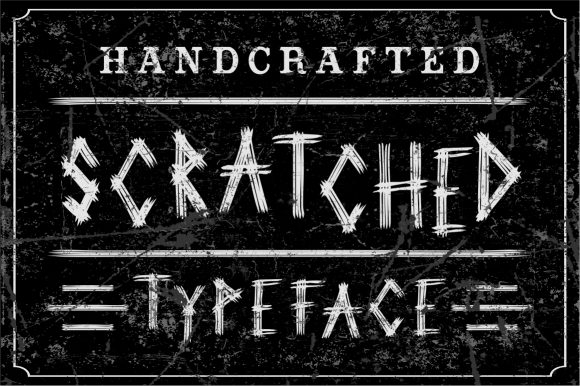
Handcrafted Scratched Typeface
Die richtigen Designelemente zu finden, kann eine Herausforderung sein, aber Handcrafted Scratched Typeface bietet eine außergewöhnliche Sammlung, die Ihre Arbeit sofort aufwertet.
Egal, ob Sie POD-Produkte (Print on Demand), Hochzeitseinladungen oder Social-Media-Grafiken erstellen, Handcrafted Scratched Typeface ist die ideale Wahl.